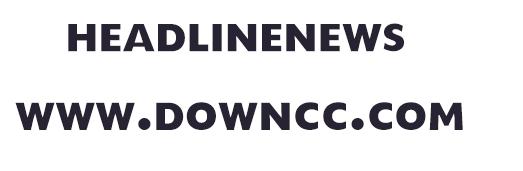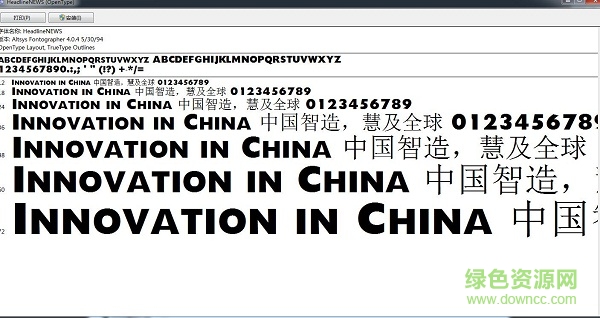
headlinenews字體是一款渾厚醒目的英文無(wú)襯線(xiàn)字體,字形飽滿(mǎn),輪廓清晰,氣勢(shì)恢宏,多用在新聞、期刊、雜志的大字標(biāo)題處,歡迎需要的朋友下載體驗(yàn)!
顧名思義,幾何無(wú)襯線(xiàn)體是基于幾何形狀的,透過(guò)鮮明的直線(xiàn)和圓弧的對(duì)比來(lái)表達(dá)幾何圖形美感的一種無(wú)襯線(xiàn)字體。